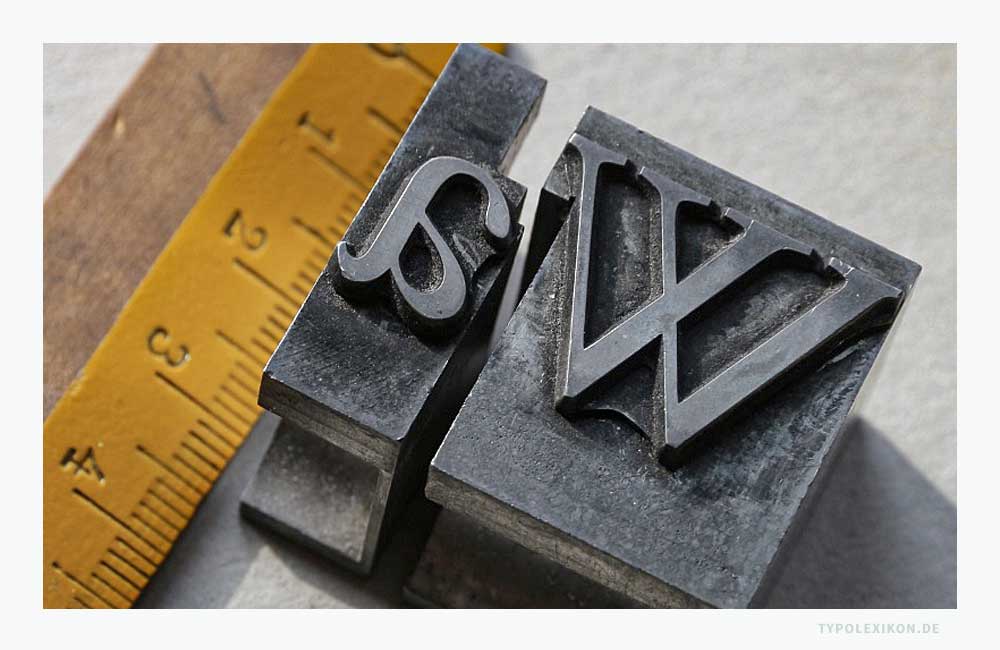
Unterschneiden
Typografischer Fachausdruck aus dem gewerbespezifischen Sprachschatz dspr. Schriftsetzer, Schriftgießer und Drucker aus der Periode des materiellen Schriftsatzes mit physischen Drucktypen aus Metall (z.B. aus einer Blei-Zinn-Antimon-Kupfer-Legierung) für die selektive Verringerung der Schriftlaufweite einer dicktenindividuellen Druckschrift, ausgehend vom normalen Breitenlauf bzw. der Normalschriftweite (NSW); Verringerung des Zeichenabstands oder Wortzwischenraums; eng. »Font Kerning«; CSS-Eigenschaft »font-kerning«. In der Schriftgestaltung zählt das Unterschneiden zur Zurichtung einer Schrift, in der Mikrotypografie ist es eine Form des Optischen Schriftweitenausgleichs (OSW).
Im optomechanischen Lichtsatz (Fotosatz), im Desktop Publishing (DTP) und im E-Publishing (Online-Publikationen) wird im dspr. Raum für »Unterschneiden« bzw. »Unterschneidung« überwiegend der Anglizismus »Kerning« verwendet.
Neben ästhetischen Motiven (z.B. individuelles Unterschneiden einer Wortbildmarke, Headline oder eines Werbeslogans) ist der Zweck des Unterschneidens die optische Korrektur von kritischen »Unterschneidungspaaren« bzw. »Kerning-Paaren« einer Proportionalschrift, um dadurch ein harmonisches Schriftbild zu erzielen und/oder die Lesbarkeit einer Druckschrift bzw. eines Screen Fonts zu optimieren.
Für das manuelle Unterschneiden im Feinsatz gibt es unterschiedliche Gründe, beispielsweise:
Unter Unterschneiden bzw. Unterschneidung kann sowohl die systematische als auch die selektive Verringerung des Abstands von Buchstaben, Arabischen Ziffern bzw. der Satzzeichen (Zeichenabstand-Kerning) zueinander und der Wortwischenräume (Wortabstand-Kerning) verstanden werden.
Manuelle Korrektur der Schriftsatzästhetik durch eine negative (-LW) Laufweitenveränderung zwischen den kritischen Buchstabenpaaren VA und DA. Beispiel gesetzt im Photoshop® von Adobe® in der Celeste Caps (1995) von Christopher Burke, Publisher FontFont. Obere Zeile: Normalschriftweite (NSW) spationiert in +120/1000 Geviert. Untere Zeile: NSW spationiert in +120/1000 Geviert mit Unterschneidungen zwischen V und A mit -140/1000 Geviert und zwischen D und A mit -75/1000 Geviert. Infografik: www.typolexikon.de
Manuelle Korrektur der Schriftsatzästhetik durch eine negative (-LW) Laufweitenveränderung zwischen den kritischen Buchstabenpaaren VA und DA. Beispiel gesetzt im Photoshop® von Adobe® in der Celeste Caps (1995) von Christopher Burke, Publisher FontFont. Obere Zeile: Normalschriftweite (NSW) spationiert in +120/1000 Geviert. Untere Zeile: NSW spationiert in +120/1000 Geviert mit Unterschneidungen zwischen V und A mit -140/1000 Geviert und zwischen D und A mit -75/1000 Geviert.
Bleisatz
Im materiellen Schriftsatz ist im dspr. Raum charakteristisch der Begriff Unterschneiden bzw. Unterschneidung gebräuchlich. Unterschneidungen können einerseits während des Gießens einer Drucktype in Form einer »Unterschneidungsligatur« entstehen, anderseits während des Handsatzes durch das Beschneiden des Fleisches eines Schriftkegels im normalen Breitenlauf. 1)
Wortzwischenräume zählen im materiellen Schriftsatz zum Blindmaterial, das in unterschiedlichen Gevierten verfügbar ist.
Semantisch rührt »unterschneiden« von »unten schneiden« zu »unten abschneiden«. Gemeint ist hier buchstäblich das Abschneiden des »Fleisches« eines Schriftkegels mit einem Bleimesser (Handwerkermesser) und/oder ggf. mit einer Feile bis hin zum erhabenen Buchstabenbild des Kegels, um die Buchstaben dann näher aneinander »setzen« zu können.
Der Begriff »Unterschneidung« stammt aus dem Handsatz. Denn das »Unterschneiden« entstand buchstäblich durch das Abschneiden des Fleisches eines Schriftkegels mit einem Bleimesser (Handwerkermesser) und/oder ggf. mit einer Feile bis hin zum erhabenen Buchstabenbild des Kegels, um die Buchstaben dann näher aneinander »setzen« zu können.
Unterschneidung der physischen Drucktypen »W« und »a« im normalen Breitenlauf (Normalschriftweite) einer Proportionalschrift mit Serifen. Durch die Unterschneidung (Zeichenabstand-Kerning) reduziert sich der Zeichenabstand innerhalb des Unterschneidungspaars (Kerning-Paars) »Wa«. © Foto: Paul Michel, Zürich.
Unterschneidungen bei physischen Drucktypen werden nur sehr selten angewendet, weil diese – insbesondere bei umfangreichen Schriftsatzarbeiten – sehr zeitaufwändig und materialintensiv sind. Bei Werksatzschriften ist eine Unterschneidung kaum möglich, da die Drucktype zu klein für einen derartigen handwerklichen Eingriff ist. Für häufig vorkommende kritische Buchstabenkombinationen werden deshalb spezielle »Unterschneidungsligaturen« verwendet. Bei Akzidenzschriften in großen Schriftgraden (z.B. für Titelsatz) wird der Schriftkegel händisch so beschnitten, dass der erhabene Buchstabe in den Bereich des benachbarten Schriftbildes hineinragt.
Händische Unterschneidungen werden im Bleisatz mehr oder weniger als Luxus betrachtet. Sie symbolisierten im materiellen Schriftsatz einen sehr hohen typografischen Qualitätsanspruch und werden deshalb meist nur in bibliophilen Druckerzeugnissen angewendet.
Fotosatz und Desktop Publishing (DTP)
Im Optomechanischen Schriftsatz (Fotosatz) und im Desktop Publishing (DTP) werden Schriftlaufweiten stufenlos in der relativen Masseinheit Geviert gemessen und unterschnitten. Die Werte des Laufweitenausgleichs von Desktop Publishing Computerprogrammen, beispielsweise InDesign® von Adobe® oder QuarkXpress® von Quark®, weichen in der Regel voneinander ab. 2)